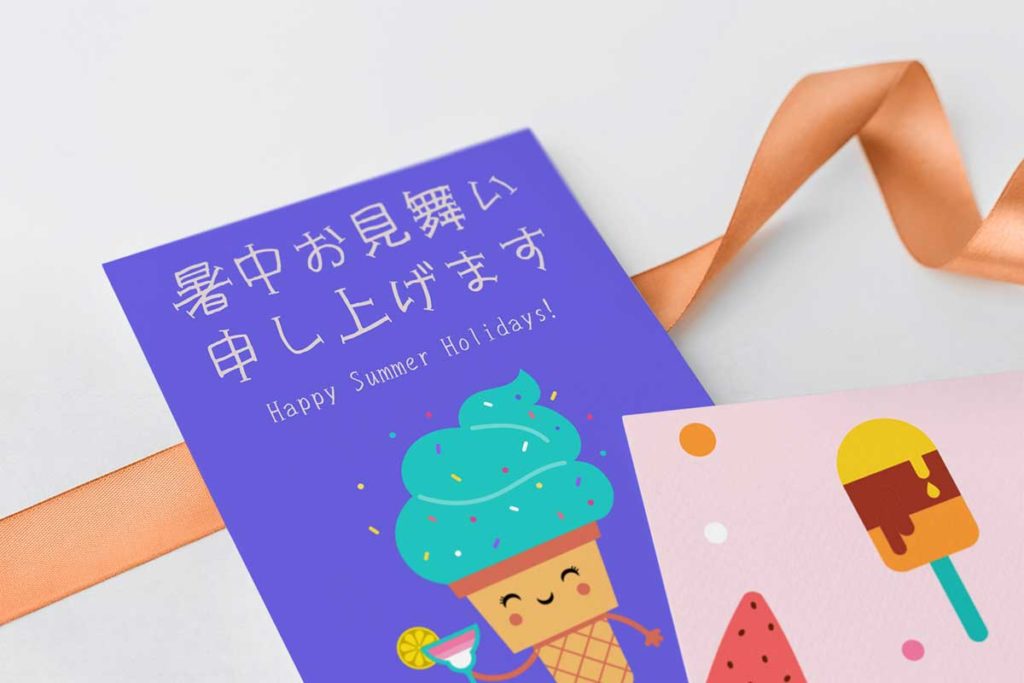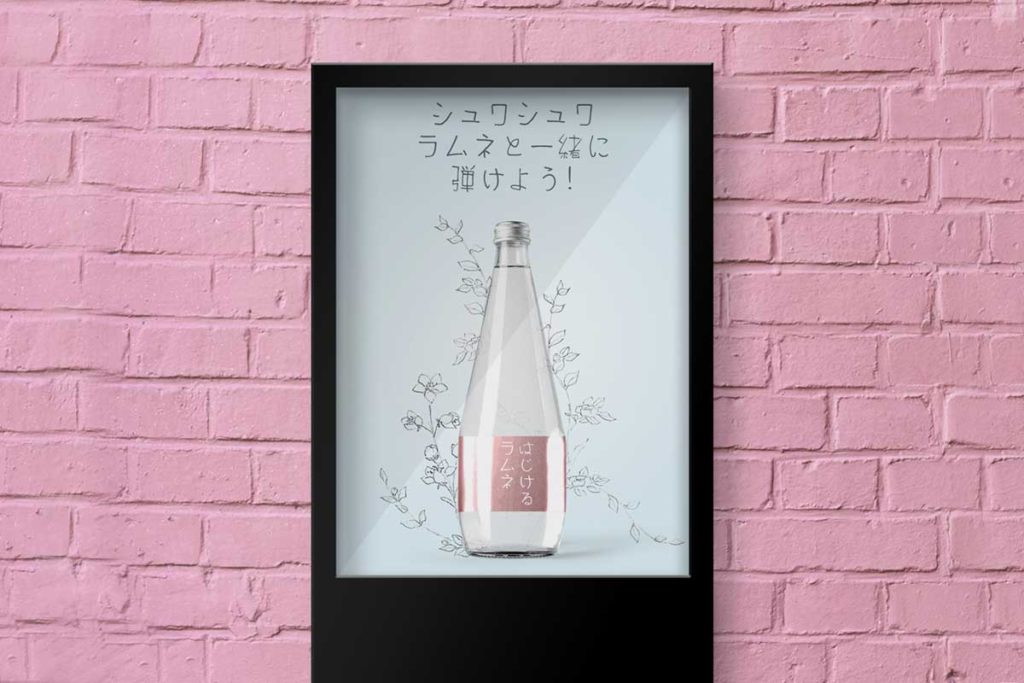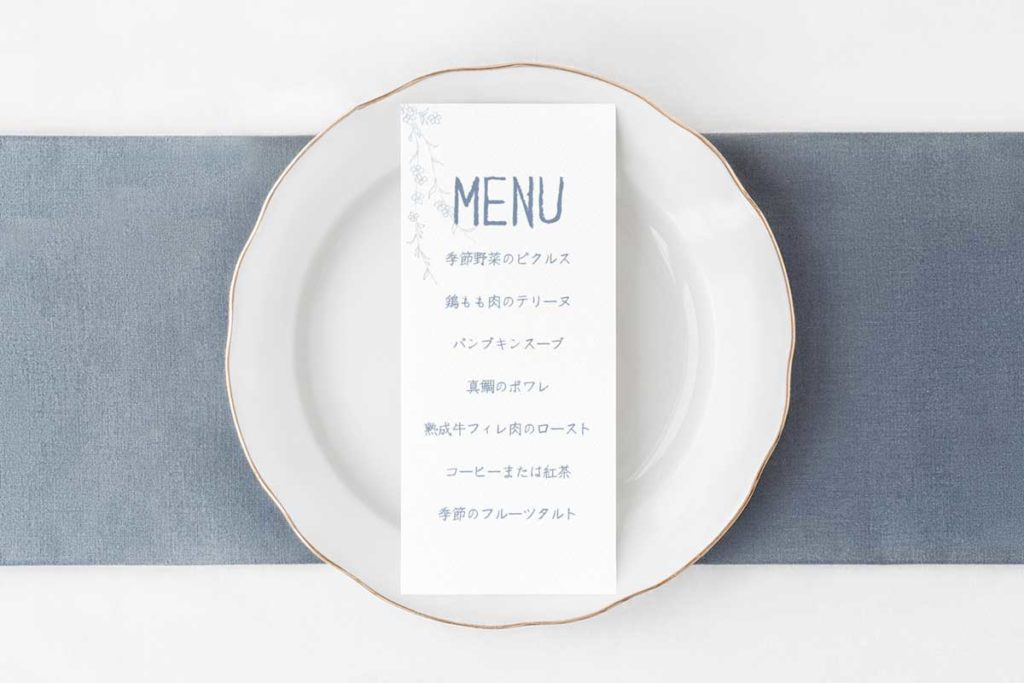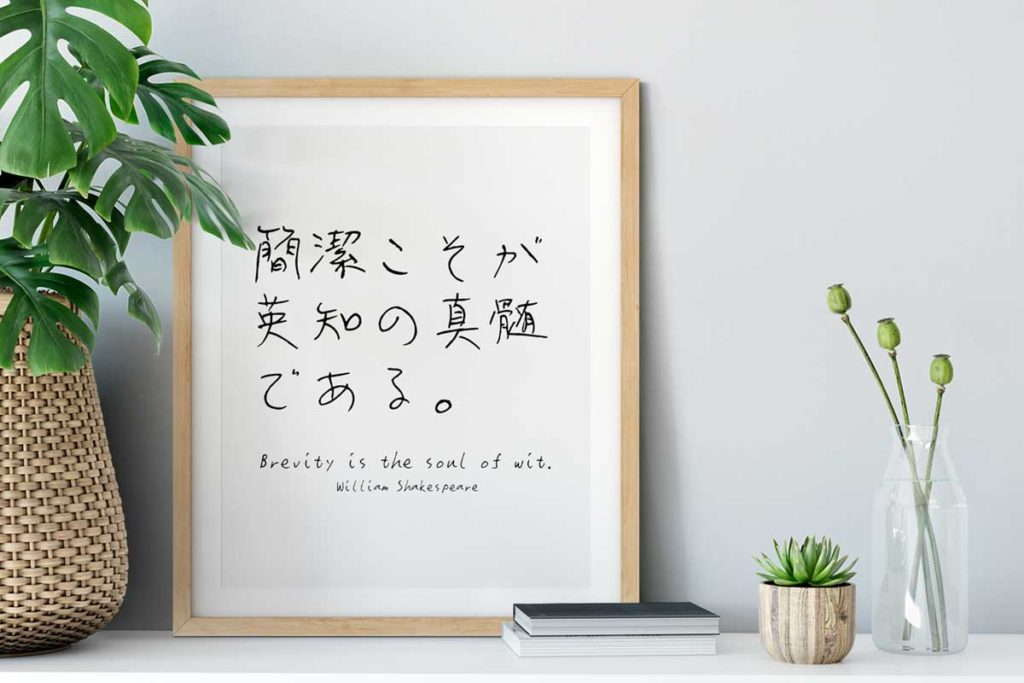
「ユニーク手書き風和文フォント完全集」の気になる中身
Windows”メイリオ”の日本語を作成したデザイナー鈴木 竹治氏監修の可読性を追求した手書きフォント竹シリーズから、手書きの様々なペン字シリーズを幅広く収録したここだけのお得なパックとなっております。
ポスター制作や同人誌など、使い方は無限大!個性豊かな手書きフォントで様々なデザインをお楽しみ頂けます。
手書き風フォントにありがちな「せっかくこのフォント使いたいのにあの漢字がない!」問題も、よほど珍しい漢字でない限り大丈夫です。
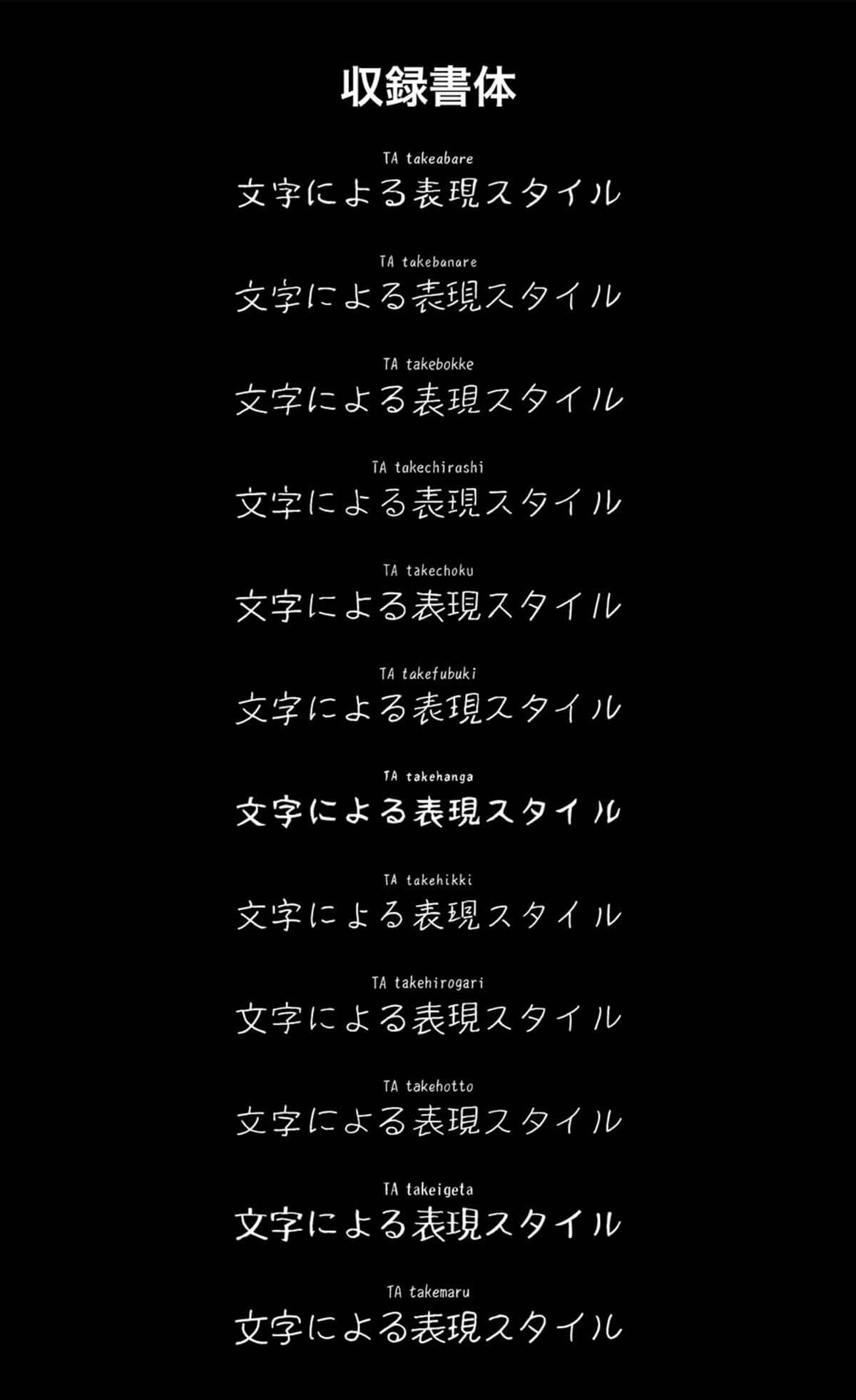
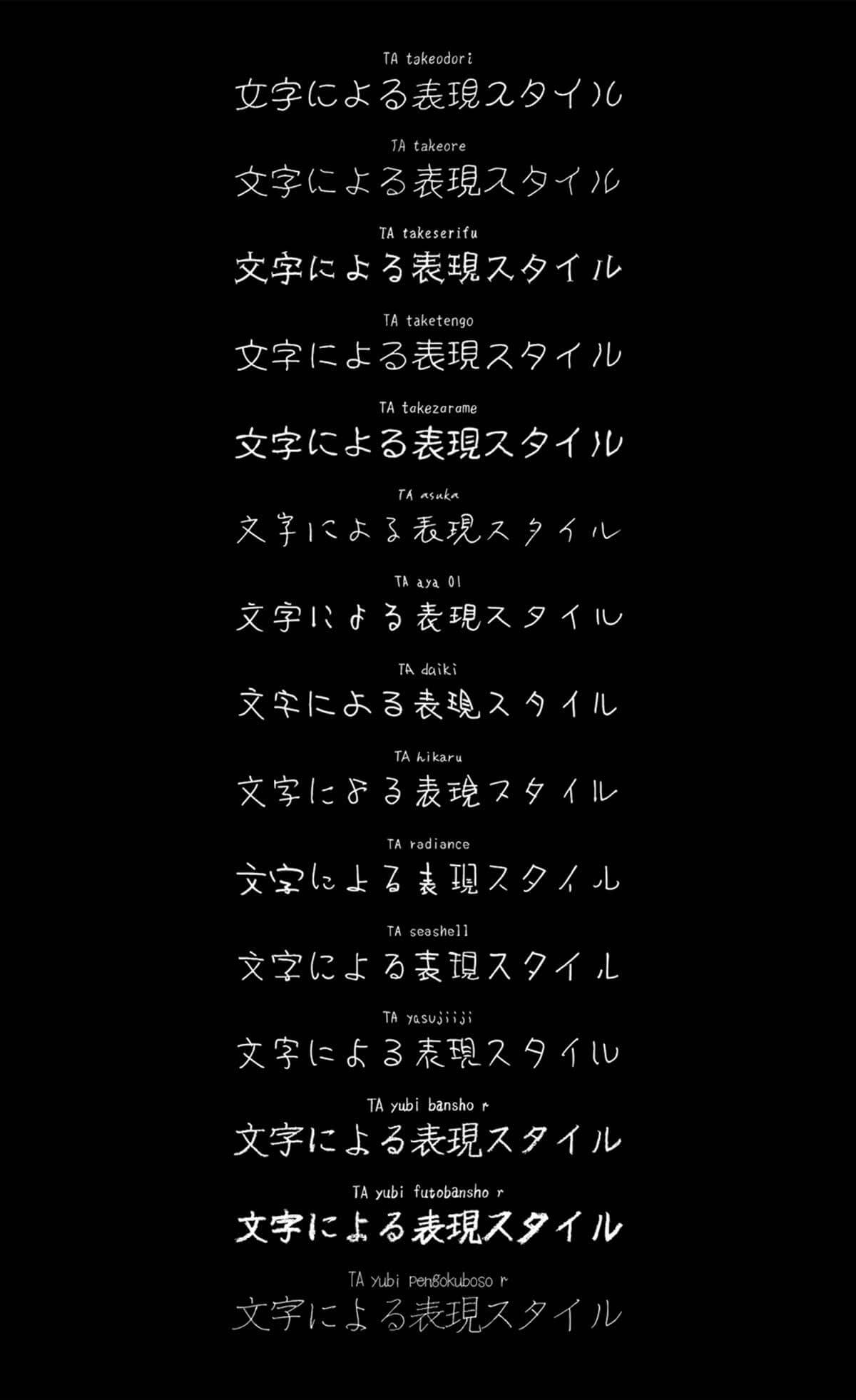
- TA takeabare
- TA takebanare
- TA takebokke
- TA takechirashi
- TA takechoku
- TA takefubuki
- TA takehanga
- TA takehikki
- TA takehirogari
- TA takehotto
- TA takeigeta
- TA takemaru
- TA takeodori
- TA takeonre
- TA takeserifu
- TA taketengo
- TA takezarame
- TA asuka
- TA aya 01
- TA daiki
- TA hikaru
- TA radiance
- TA seashell
- TA yasujiiji
- TA yubi bansho r
- TA yubi futobansho r
- TA yubi pengokuboso r